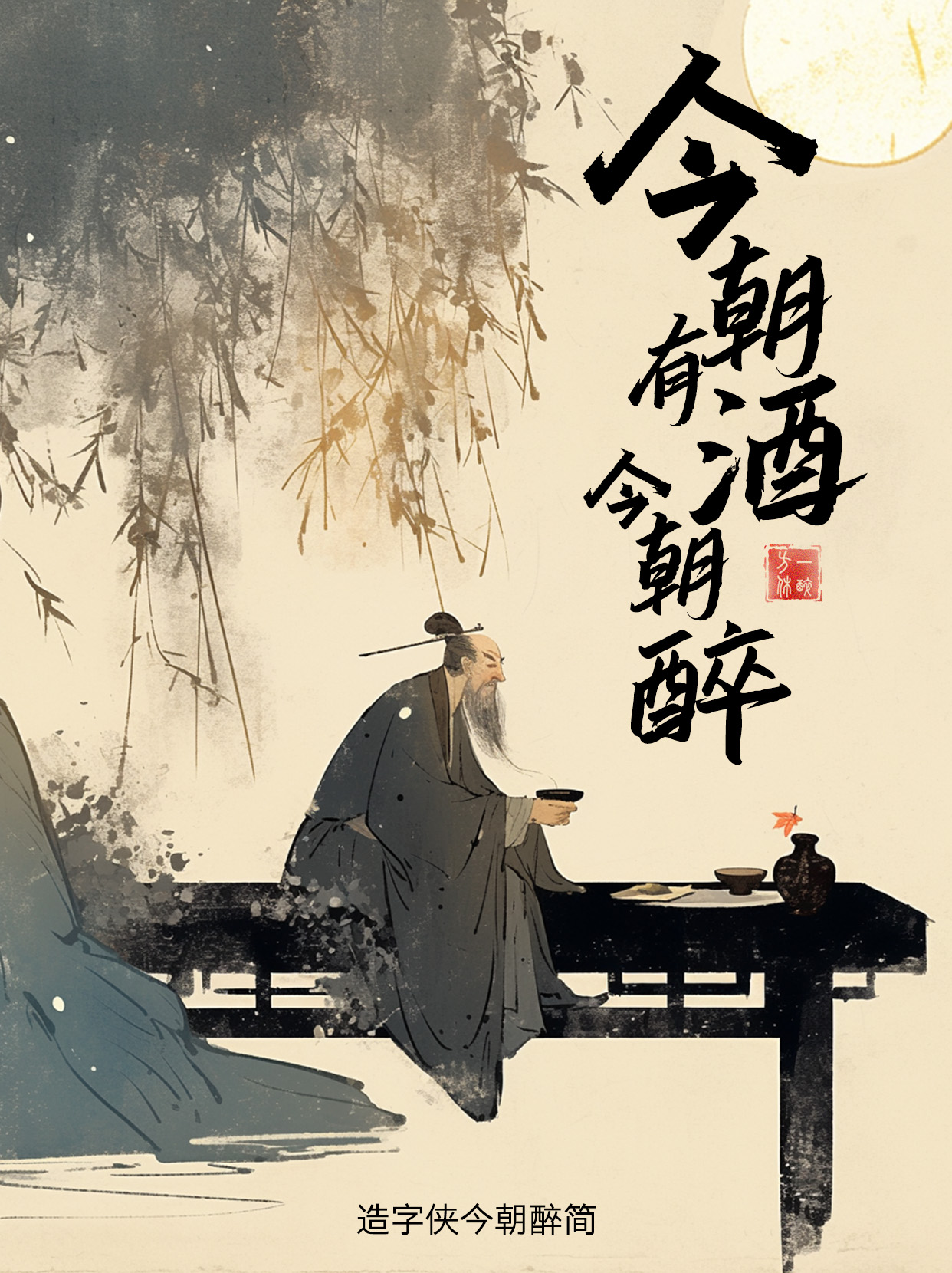
造字侠今朝醉简
PlayFont-DrunkGB
• 字体名称: 造字侠今朝醉简
• 字符集: GB2312-1980
• 字体语言: 简体
• 书体类型: 毛笔字体
• 字体类型: 普通字体
• 字体字重: 常规(Regular)
毛笔楷书字体,收笔潇洒凌厉,如醉酒一般,笔法正统酣畅,劲健雄浑。适用于白酒包装等场景。